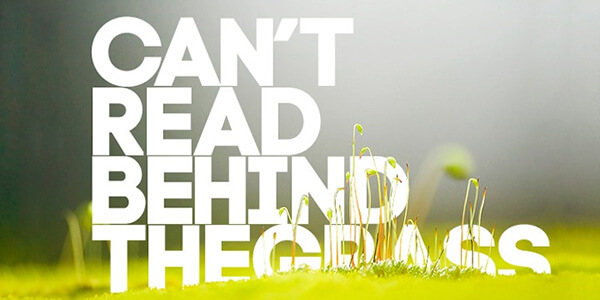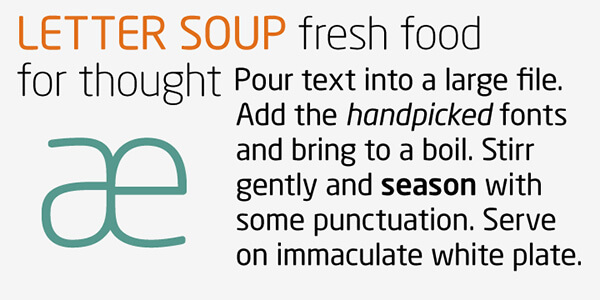
フォントの歴史からSan Serifの発展を知る Webに適したフォントとは?無料で使える人気のフォント集
San Serifは生まれてまだ100年程度で、デザイナーや書体マニアなら起源を知っておきたい。現在知られている情報では、現代のSan Serifはウィリアム・キャスロンが1816年にイギリスのフォントメーカーにて創り出したフォントである。当初文字サイズは28のみで、大文字のみ利用可能であった。キャスロンは、San Serifが広まるという自信はなかった。というのも、初代のSan Serifのデザインは全く魅力的ではなかったからである。
そして創り出されたのはAkzidenz Grotesk体で、ベルリンのベルトールというフォントメーカーにで生まれたフォントである。Akzidenz Groteskはその起源もデザインもずっと魅力的で、即人気になった。間も無く、他のフォントメーカーもAkzidenz Groteskに似たSan Serifをデザインするようになった。最初は見出し用に使用されたが、本文中でも使いやすいように小文字も作られるようになった。
なぜGrotesk(異様)なのか?
こういったフォントが出現した1830年代当初は、世にも異様で一般受けしなかったので、広告以外の用途では使用されることは滅多になかった。しかし、Akizidenz Groteskが使われなくなったのは、バウハウス(絵画,彫刻,建築,工芸教育に革新的な方法を用いたドイツの総合的造形学校)が全盛期を迎えるなど、芸術や商業における新たな流行が到来してからである。芸術や商業でのデザインを一新するにあたり、個性的なフォントが必須となったのだ。
San Serifの魅了
San Serifの一番の魅力が受け入れられるようになったのは20世紀初期である。美と実用性が結びつけられるようになりフォントも必要以上に飾り立てる必要性はないという考えが広まったため、シンプルなものが好まれるようになった。
ドイツの影響
Akzidenz GroteskからSan Serifが広まったのは、ドイツで誕生し発展したバウハウスのイデオロギーのおかげだろう。1928年に誕生したSan Serifの人気書体の一つにFuturaがある。Futuraの形状は幾何学そのもので、セリフ(装飾)はなく伝統的な書体に準じたデザインだ。一部では批判の声もあったが、Futuraが新旋風を巻き起こしたことは間違いない。
Futuraそのものが革命的存在であったが、フォントやデザイン界での影響や浸透はHelveticaほどのものではなかった。HelveticaはSan Serifの代表的なフォントとして世の中に知れ渡るようになった。
Helveticaはシンプルで装飾感が無く、実用的というSan Serifの重要な特徴を兼ね備えている。1957年生まれたこのフォントやUniversなどのその他のAkzidenz Groteskからの派生フォントは、Futraに見られるジオメトリックデザインにインスピレーションを受けている。
ヒューマニストフォントスタイルの発展
San Serifの発展史に見られるのは、他のフォントを真似したり盗作したり、Akzidenz Groteskなどの型破りなSan Serifを使いやすく控え目にしただけのものだと思う人もいるだろう。しかし、こういった発展は軽視されるべきではない。というのも、テキストや広告に対する捉え方、当時のデザインに大きな影響をもたらしたからである。
San Serifはクラシックなものから現在見られるモダンなものにまで、素晴らしい発展を遂げてきた。Futraのような人工味があるデザインから、Helveticaのような自然なデザインまで、San Serifはよりリベラルになり、その結果ヒューマニストフォントがトレンドとなった。
ヒューマニストSan Serifの発展は1976年に誕生したFrutigerというフォントが元になっている。このフォントは、Helveticaに似たスタイルだが、ジオメトリックとは反対に人間味あふれるヒューマニスト的特徴がある。Helveticaとの違いは大きくはないが、旧San Serif体によく見られる鋭い雰囲気を一変するものだった。その結果、ヒューマニストSan Serifはより親しみや温かみがあり、FutraやHelveticaと異なった仕上がりとなった。
Frutigerを皮切りに、ヒューマニストフォントが生まれていった。そのうちの1つは1984年に創られたMetaで細長い形状が特徴だ。この形状は実用的な目的のためのものだった。Metaの生みの親であるエリック・スピーカーマンはスペースを最大限に活用すると同時に小さなサイズでも読みやすいフォントを目指し、Frutigerを創った。
厳選!使いやすいSan Serifフォント
Maven Pro
Maven Proは初代のフリーフォントで、ジオメトリックなスタイルだ。モダンでスタイリッシュ、そしてエレガントな雰囲気が出ている。ジョー・プリンスが生んだこのフォントは、3種類の極細ウエイトがある。
Supria Sans
Supriaは広い層が使用しやすいユニバーサルデザインタイプで36種類のフォントがある。女性的な雰囲気を演出できる曲線的なイタリックやシャープなイタリックでより慣れ親しんだカジュアルな雰囲気を演出することもできる。
幅は2種類、ウエイトは6種類、フォントスタイルは3種類ある。OpenTypeでは、より文字数が多く、東西ヨーロッパの言語に対応している。
Supria Sans Condensed
Supria Sans ConsensedはSupria Sansを少しバージョンアップしたもので、同じく様々なシーンでの使用が想定されている。しかし、文字がより細いため繊細な雰囲気になっている。ウエイトは6種類、フォントスタイルは3種類で、その中でさらに微調整が可能なため、他のフォントとの相性も抜群だ。
Glaublau Sans Pro
一つのフォントスタイルにつき1000の記号、7種類のウエイト、さらに6種類の見出し用フォントがあり、様々な用途に使用できる万能フォントだ。それぞれのフォントスタイルに独自の個性や雰囲気がある。アップライト版は清潔感があり、ニュートラルでカジュアルなデザインに向いている一方、イタリック版は手書き感があり、絶妙さを要するアートに向いている。
Proxima Nova
こちらは、
• 7種類のウエイト
• 3種類の幅
• オールドスタイル
• 代替フォント
• 多言語対応
の機能が備わっている。
様々なオプションにて、目を引くデザインが可能。Glaublau Sans Pro同様、幅広いタスクに使用でき、控え目なニュアンスを表現するのにもタイトルを目立たせる様にboldタイプを使うのも良い。
Brandon Grotesque
このフォントはユニークなデザインを創り出すのにぴったりだ。微妙にノスタルジックな雰囲気の中にも、アール・デコ風の個性的なデザインに仕上がっており、見ていて楽しい。
ジオメトリックな形状をを見事に読みやすくエレガントに仕上げており、もちろんヨーロッパの様々な言語に対応している。
Museo Sans
このフォントはコントラスト(文字の幅)が小さく美しいジオメトリーフォントだ。読みやすく、本文にもタイトルにボリューム感を加えるのにもよい。フォントでは、
• リガチャ
• オールドスタイル
• 分子・分母
• 上付き文字・下付き文字
が使用可能。
Automatic fractionも備わっており、中央ヨーロッパの言語にも対応している。
Futura
FuturaはSan Serifの中でも最も人気書体の1つだ。モダンなジオメトリースタイルで、20世紀半ばの雰囲気も残しつつ、見事に現在のトレンドにもマッチしている。万能性は抜群で、light italicからextra black condensed italicまでに及び10種類のスタイルがある。ウエイトは全ての文字で統一されている上、真円や二等辺三角形もある。
Halis Grotesque
8種類のウエイトがあってアップライトとイタリックがある。文字間のスペースが広いので、小さめのフォントでもとても読みやすい。
• スモールキャップ
• オールドスタイル
• 化学式用下付き文字
• 上付き文字
• 代替スタイル
が取り揃っている。
Intro
Introは様々なサイズやスタイルのフォント、また、紙媒体でもウェブ媒体でも読みやすいのが特色だ。50種類ものバリエーションに富み、それぞれに最適なカーニングが施された、ジオメトリックなフォントである。多種多様な言語をサポートし、文字やグリフも幅広く取り揃っている。また、タイトル重視のデザインにぴったりだ。
Neue Helvetica
Neue Helveticaは繊細なUltra Lightから、しっかりとしたBlackまで50種類のフォントウエイトがある。万能でとてもニュートラルだ。現在はグラフィックデザイナーに最も人気のある書体の1つで、ライセンスはウェブ、デスクトップ、アプリ、電子書籍に適応している。
Swiss 721
Swiss 721は売れ行きナンバーワンのフォントの一つ。従来のSan Serif屈指の特徴を兼ね備えているというのは当然だろう。上品さがあり、ニュートラルなフォントだ。様々なヨーロッパ言語においてテキストと共にグリフが使用可能だ。
Avenir
80年代後半に作られたフォントだが、今も尚デザイナーが愛用している。リニア体でFuturaやErbarをインスピレーションとしたものである。しかし、スタイルのニュアンスはこの2つのフォントとは異なり、独自の魅力がある。多様なテキストにて読みやすく、簡単にスキャン可能なのだ。light からblackまで、6種類のウエイトで使用可能。
Grotesque
Grotesqueはジオメトリックでハイテクな雰囲気が漂っている。丸みを帯びた形なので、温かさがあり親しみやすい書体だ。
• 14種類のフォントスタイル
• 7種類のウエイト
• OpenType
• イタリック
が選択可能だ。
紙媒体のメディア、多種多様な出版部、グラフィックデザインに向いている。
News Gothic
News Gothicは20世紀初頭に初めて登場した、クラシックなSan Serifである。見事にデジタル化され、様々な目的に使用できるものへと進化していった。ポスターのヘッドラインを可愛らしくする目的から、ウェブサイトのタイトルを目立たせる目的までと用途は拡大してきた。フォントスタイルは15種類で基本フォーマットは2種類である。
San Serifのカテゴリー
1800年代から現在まで、San Serifは急進的なもの、さりげないもの、実用的なものなど様々な変化を遂げてきた。今日では、San Serifの分類基準は明確になっている。
• Grotesqueは、垂直カーブを特徴とする、目を引くスタイルだ。
• Transitional sans serif はHelveticaを始めとるすモダンなスタイルである。San Serifで最も多いタイプのもので、まっすぐとしており、画数も少ないのが特徴である。
• Humanist sans serif はVerdanaやCalibriなど筆書きっぽさが特徴で、読みやすくなっている。
• Geometric sans serifはFuturaやSpartanのように、ジオメトリックな書体で、大変モダンな印象だ。角張った形状なので、テキストでの使用頻度はSan Serif体の中で一番低くなっている。
San Serifは今後も成長し続け、新しいフォントを生み出したり、既存のものアレンジしていったりする中で、新たに貴重な発見があるだろう。